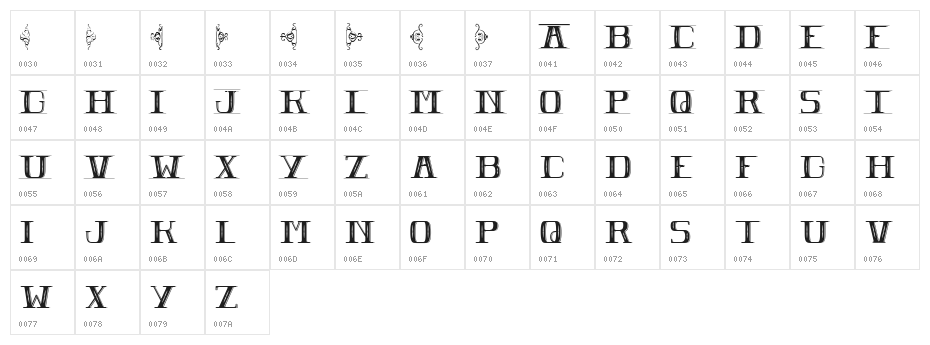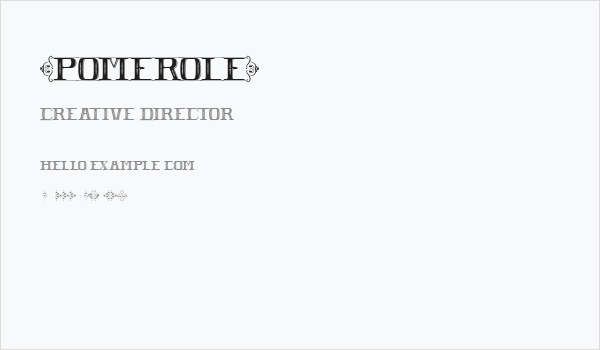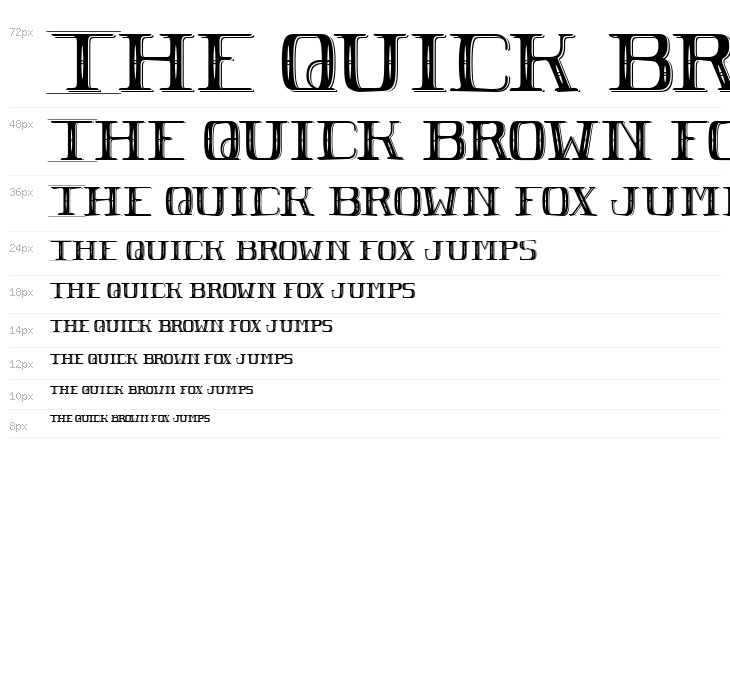
6POMEROLE7 Font
| Progetti proposti | Ideal for use in vintage-themed designs, wedding invitations, historical documents, or any project requiring a touch of elegance and sophistication. |